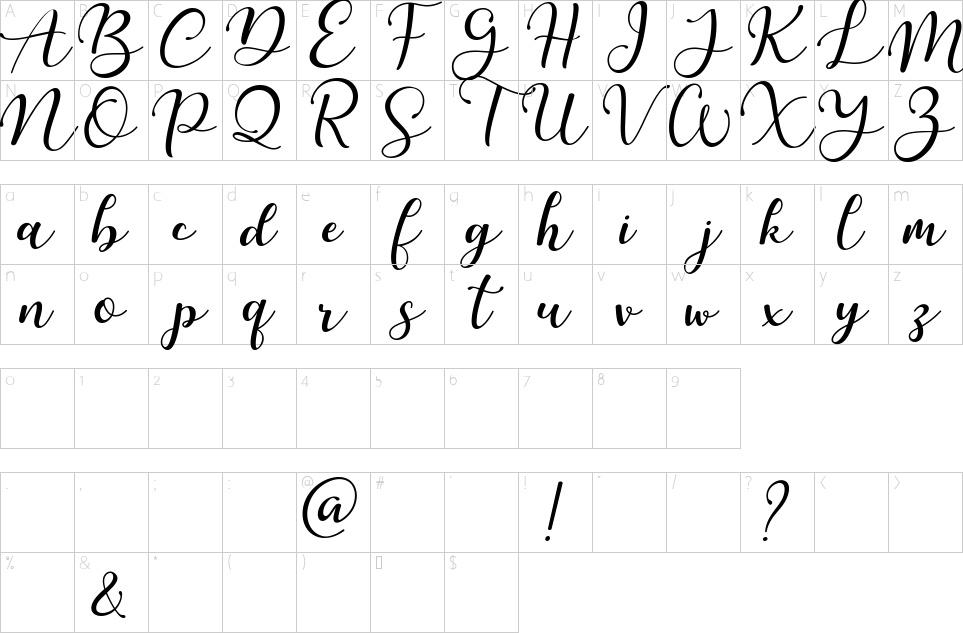
Descubra Martinesse, uma elegante fonte gráfica que enriquece seu design de forma única. Desenvolvida por Sronstudio, Martinesse oferece uma escolha semelhante a fontes de qualidade paga, mas sem o custo adicional. Esta fonte foi projetada para criar textos envolventes e atraentes, adequada tanto para textos de marca quanto para materiais gráficos de design personalizado. Com 1,684 downloads, Martinesse é uma escolha popular entre os designers que buscam uma fonte de qualidade para projetos que vão além do básico. Seja para criar letras memoráveis em sua próxima página ou para personalizar seu aplicativo de design favorito, Martinesse é a escolha certa para quem busca um toque único em seus projetos. Descubra agora e dê vida ao seu design.